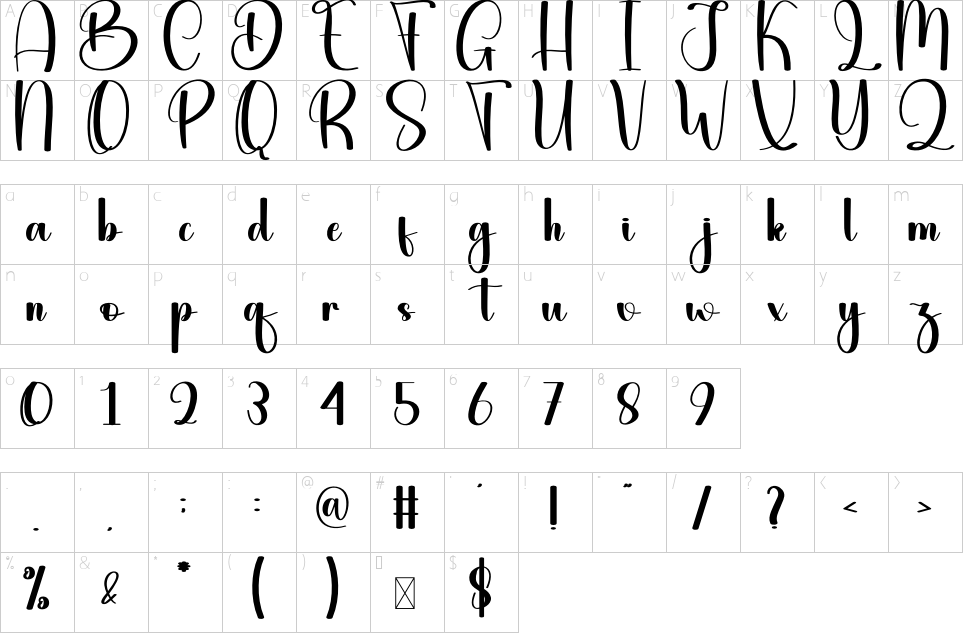
Aqui está uma versão curta e envolvente para a página de download da fonte ‘Dating Font’: O Dating Font é uma opção elegante e moderna para aqueles que buscam uma maneira criativa de personalizar suas mensagens online ou anúncios. Desenvolvida por um talentoso designer desconhecido, esta fonte proporciona um toque diferenciado no meio do movimento constante da internet de hoje. Com seu design cuidadosamente elaborado, o Dating Font é ideal para quem busca algo único e versátil para complementar suas postagens no site de encontros. Seja para mensagens em aplicativos de correspondência ou anúncios online para casamentos virtuais – a ‘Dating Font’ certamente terá seu lugar. Esta fonte está disponível tanto para sistemas Windows quanto Mac, tornando-a uma escolha conveniente para todos aqueles que buscam uma adição sofisticada à sua digital signature. Com apenas 803 downloads desde seu lançamento, o Dating Font já provou seu valor como um recurso gráfico indispensável e divertido no mundo virtual do internet dating.